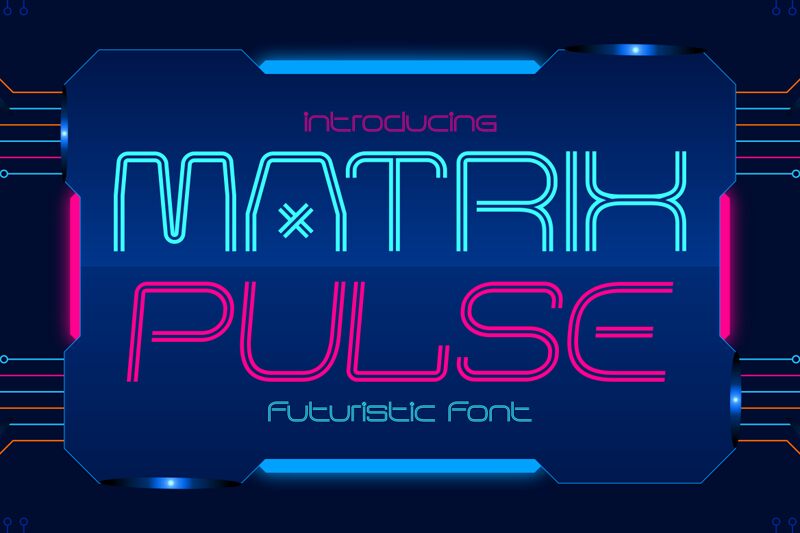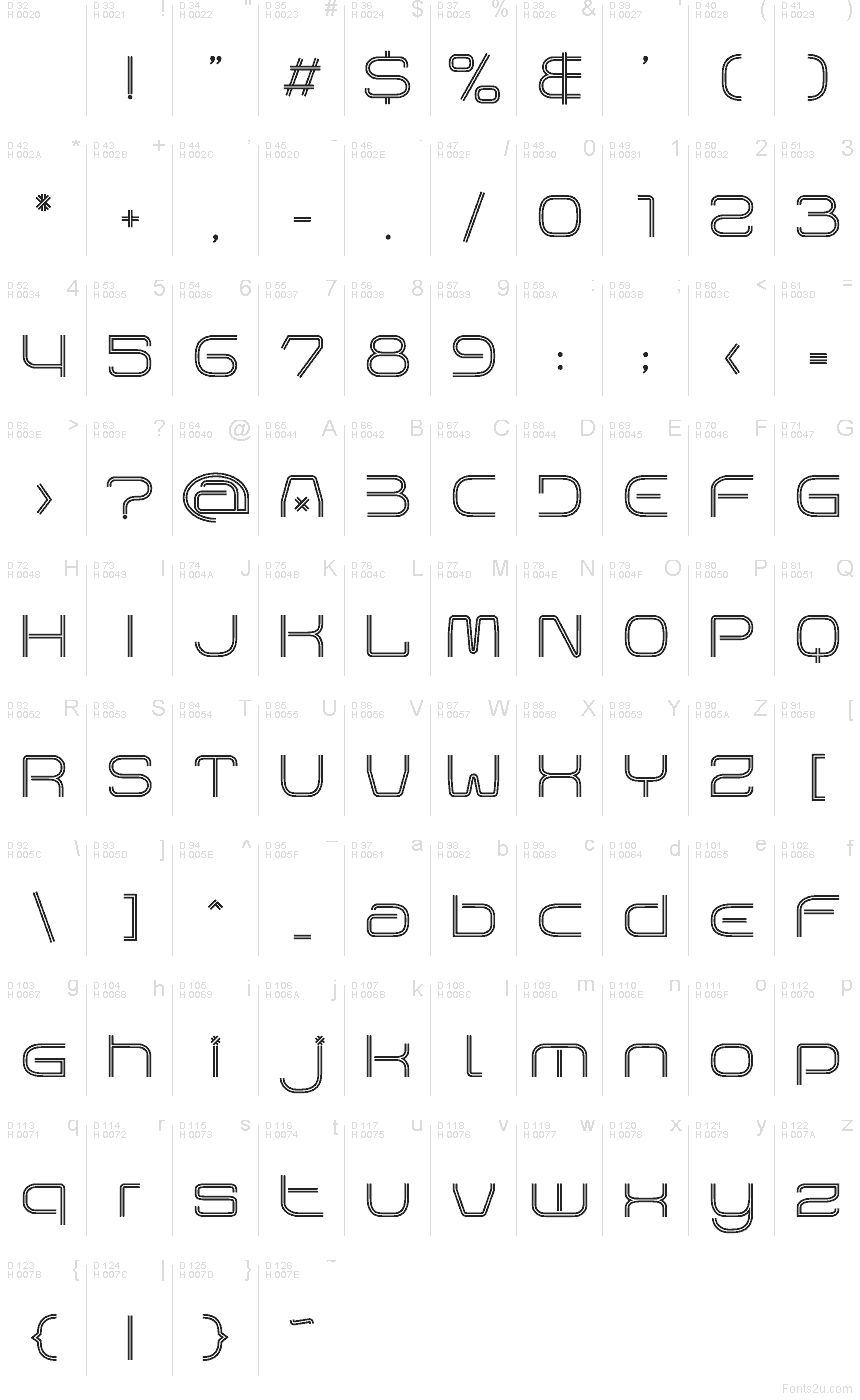
Matrix Pulse od Shanaf Studio to darmowy, futurystyczny font typu display, utrzymany w klimacie układów scalonych. Litery zostały zbudowane z zaokrąglonych, równoległych linii, które płynnie przechodzą w łagodne narożniki i otwarte ścieżki. Dzięki temu alfabet zyskuje żywy, świetlisty rytm, daleki od surowych, sci-fi krawędzi.
Sprawia to, że font świetnie pasuje do brandingu gier, opraw muzycznych, plakatów wydarzeń technologicznych, pasków tytułowych w interfejsach czy nagłówków, gdzie kształt liter przejmuje rolę głównego elementu graficznego. Jako darmowy font, najlepiej sprawdza się w krótkich nagłówkach, logotypach i na grafikach tytułowych, zwłaszcza gdy szukasz gładkiego, elektronicznego wyglądu bez efektu przesadnej mechanizacji.